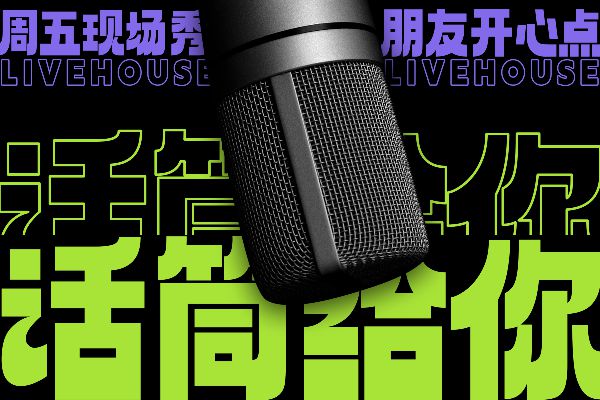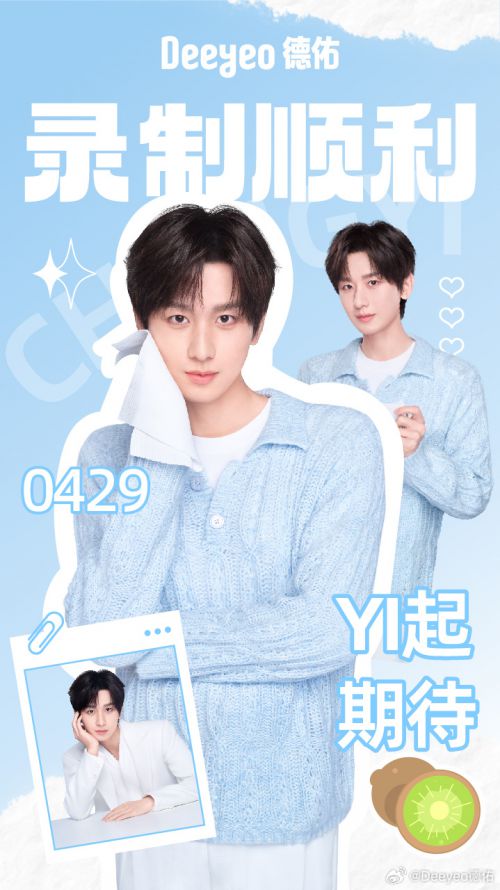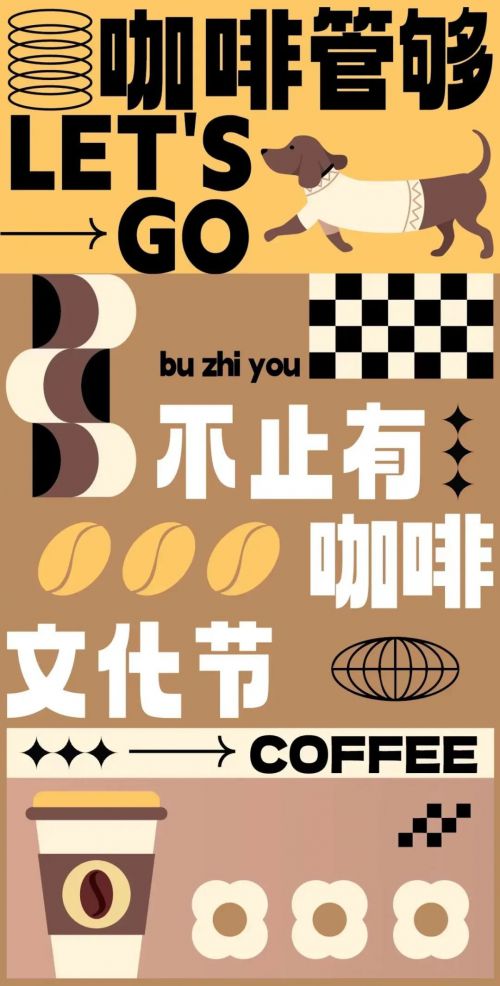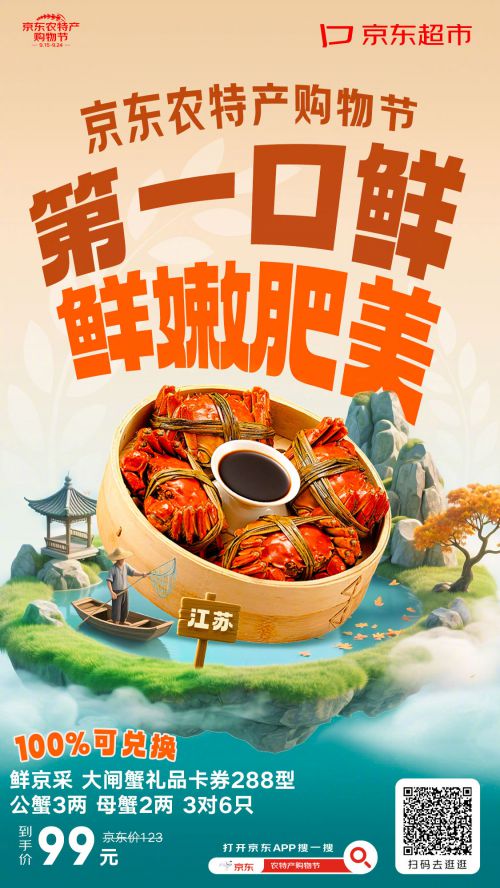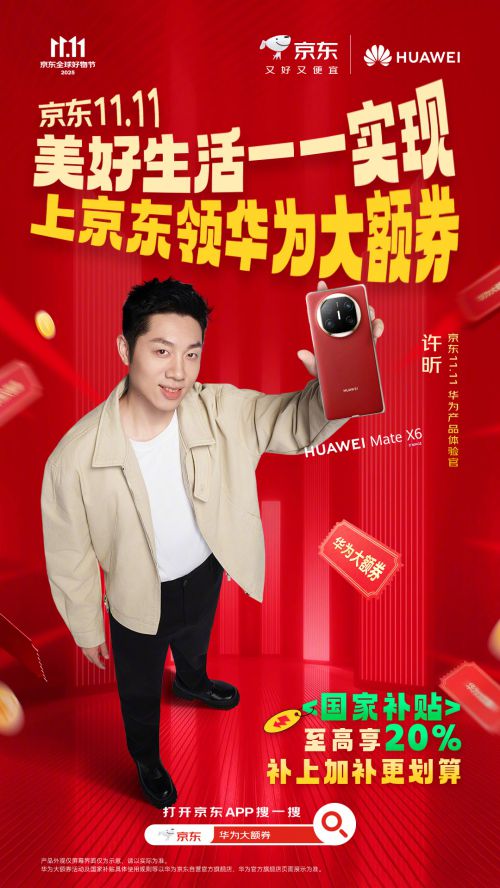
厚底黑是Aa字库推出的一款创意风格免费商用字体,以力量与复古为核心设计理念,兼具视觉冲击力与实用价值。 字形方正大气,重心居中,中宫宽博的布局让字体舒展不局促;笔型采用利落直角,笔画方头分明,粗细均匀的线条中藏着逆反差巧思——底部特意加粗的处理,为字体注入沉稳的力量感,仿佛稳稳扎根的基石。部分字形通过对称结构增强平衡美,笔画转折处融入灵动曲线,中和了厚重感,增添复古活力,让“力量”与“活泼”巧妙融合。 作为标题字表现亮眼,适用于运营宣传、海报主视觉、综艺娱乐包装等场景,无论是传递品牌态度还是营造复古氛围,都能精准传达。免费商用的授权范围,让设计师无需担忧版权问题,轻松将这份独特的力量与复古格调融入创作。